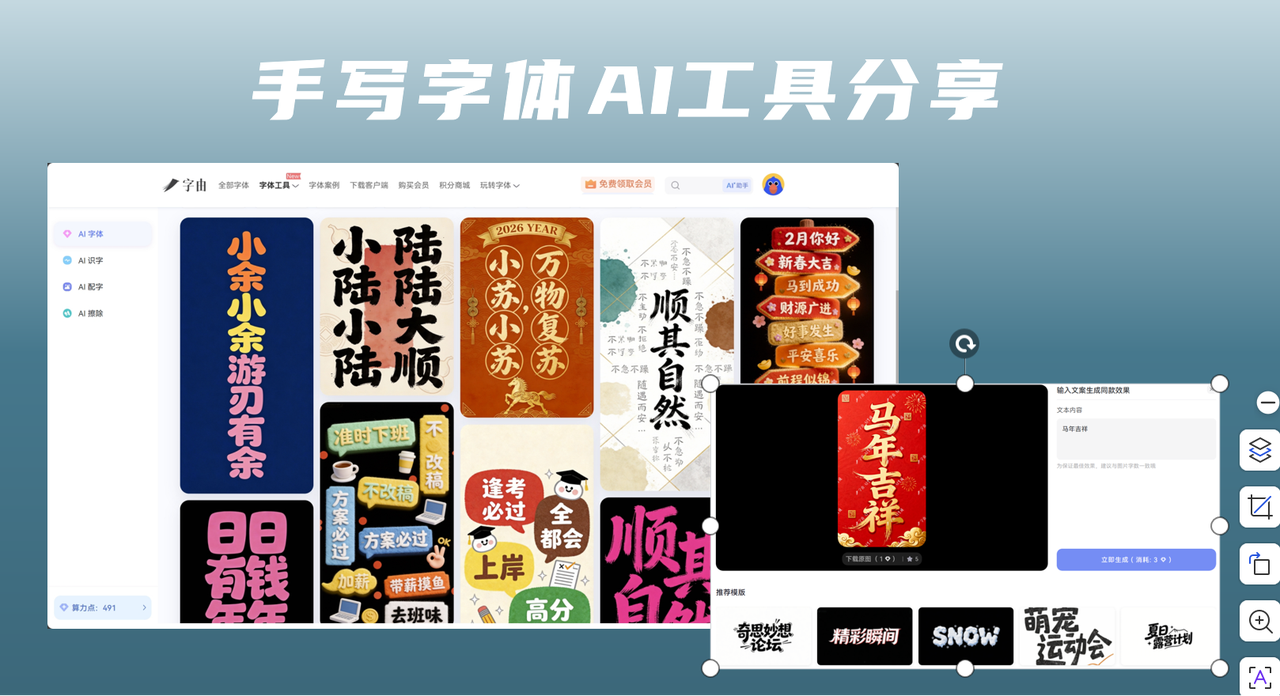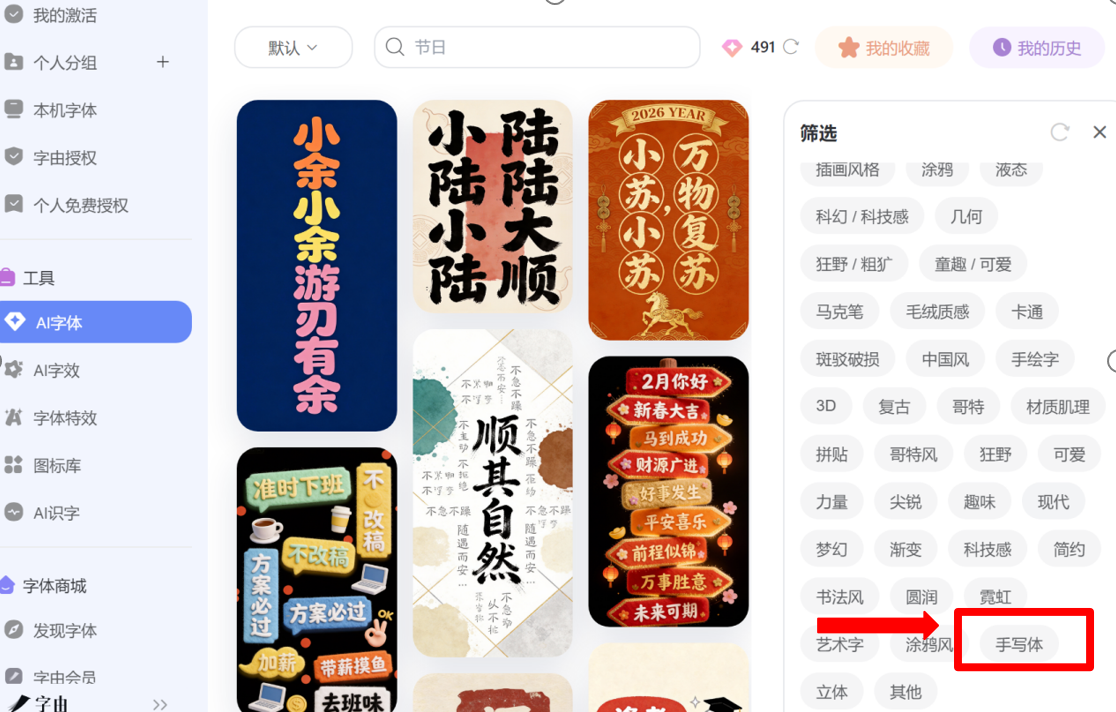
2026 最好用的手写字体 AI 推荐
在设计创作、日常办公或校园场景中,手写字体总能传递出独特的温度与个性,摆脱印刷体的刻板感。但传统手写字体库风格单一,定制化难度高,而AI技术的迭代,让手写字体的生成、识别与个性化适配变得高效便捷。2026年我实测了多款在线平台,挑出4个实用性拉满的,从专业设计到日常刚需全都覆盖。
一、字由网
字由网在2026年持续升级AI能力,字由网新上线的“AI字体”功能可以轻松帮你搞定手写字体,也是我试过几个字体生成器中最好用的一款AI字体工具,操作也非常方便。
打开字由网的官网,在首页顶端找到“字体工具”,点击“AI工具”后,我们能看到有非常多的AI字体模板。可从海量手写风格模板中挑选,涵盖工整笔记风、潦草随笔风、书法手写风等多种类型,适配海报设计、新媒体配图、手写笔记复刻等多场景
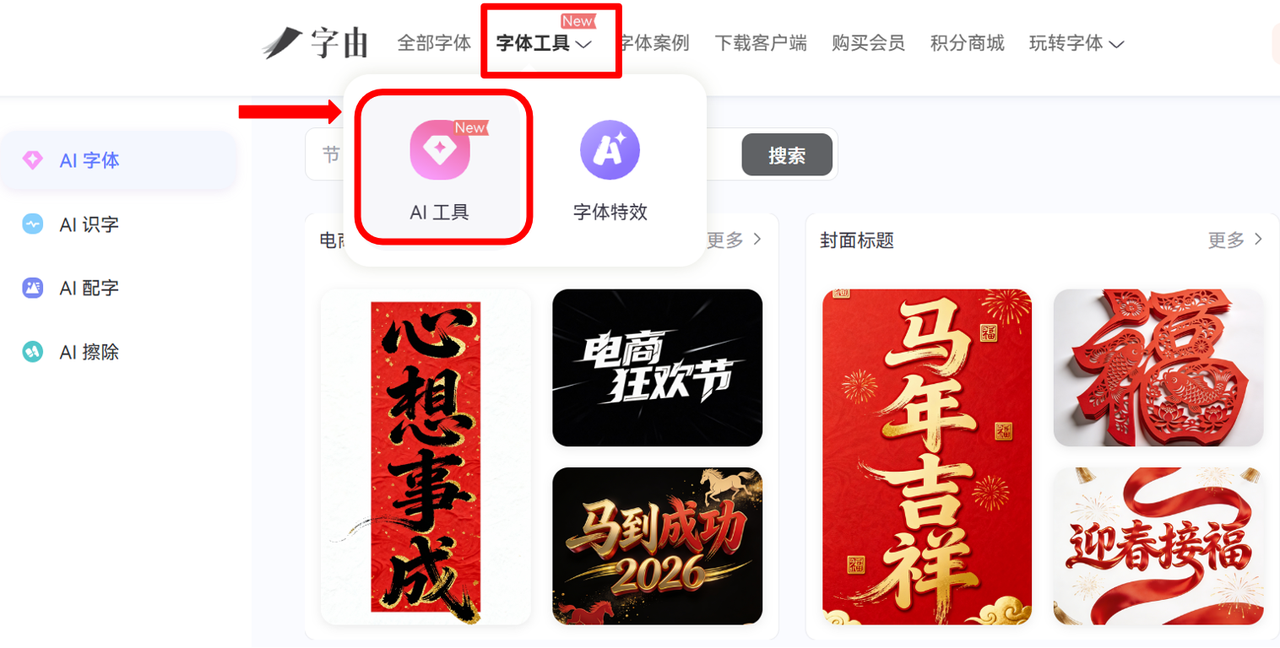
当然,为了节省时间,你也可以直接从风格分类中找到“手写体”,精准定位到手写字体AI,选择你喜欢的手写体风格。
选择好喜欢的手写字体模板后,点击生成同款。在右侧的文本内容中输入文案,但是要注意,输入的字数不能超过图片上的字数哦~点击“立即生成”等待几秒就可以得到你想要的同款手写字体啦。
而且字由的手写字体AI风格非常多,完全能满足大家的风格需求,快来挑选试试看你想要的AI手写字体吧~
二、凹凸工坊
凹凸工坊是一款主打“手写稿转换”的AI网站,尤其适合需要复刻手写文稿的场景,堪称学生与职场人的“手抄救星”,操作门槛极低,无需任何设计基础。它并非一个完全的字体网站,而是将文档转手写体,支持上传Word、TXT等格式文档,一键转换为手写稿图片,不仅提供多种手写字体可选,还能搭配高清实拍纸张背景,还原笔记本、稿纸等真实质感。
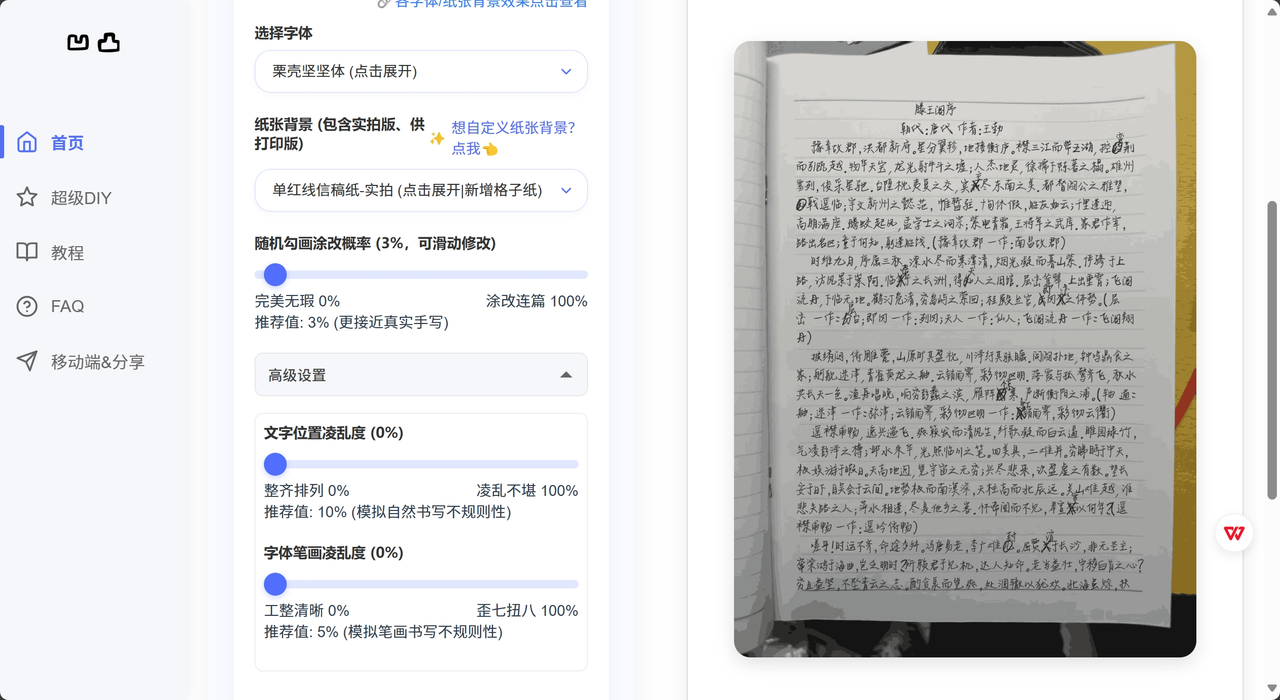
三、字体家AI神笔造字
字体家的AI神笔造字主打“专属手写字体生成”,这款工具能让用户生成带有自己笔迹特色的手写字体库,适合追求个性、需要专属手写标识的人群。打开网站后选择屏幕设计模式,调整笔画粗细与风格偏好,然后书写八个核心汉字,AI会通过深度学习分析用户的运笔习惯与字形结构,进而生成手写字体。生成后可预览任意文案的效果,还能调整字间距、行高,适配不同使用场景。
四、Refont AI
Refont AI是一款主打多风格字体生成的AI平台,2026年新增多款小众手写风格,适合追求差异化创意的创作者,同时支持中英文手写字体生成,适配更多场景。核心功能包括手写字体生成与签名定制,输入文本后,可选择优雅随笔、复古手写、卡通手写等多种风格,还能模仿真实手写效果,用户可上传自己的手写样本,让AI生成相似风格的字体,满足个性化需求。